모든 작은 것들을 위한 디자인, 아트디렉터 이주승
<블링>과 <DAZED>의 아트디렉터로 활동하고 올해 3월부터 ‘에브리리틀씽(every.little.thing)’이라는 이름으로 디자인 스튜디오를 운영하기 시작한 이주승 디자이너를 만나고 왔다. 국내 대표적인 클럽컬처 매거진과 패션 전문 매거진의 아트디렉터로 오랜 시간 일했지만, 겉 멋에 빠져있다거나 거친 사람처럼 느껴지지 않았다. 그는 스튜디오 공간 곳곳을 직접 꾸미고 다듬을 정도로 취향이 확실하고 꼼꼼하다. 그의 손이 닿지 않은 부분이 없다. 모든 작은 것들까지.
안녕하세요. 폰트클럽 독자 여러분을 위해 간단한 본인 소개를 부탁 드립니다.
안녕하세요. <블링>(www.thebling.co.kr)과 <데이즈드>(www.dazeddigital.co.kr) 매거진을 디자인하고 한동안 게임 회사 넥슨의 기업 디자이너로도 일했던 이주승입니다. 게임 회사 디자이너의 처우나 환경이 나쁘진 않았지만 지난 달 일과 작년 일을 비슷하게 작업해야 하는 반복 작업을 견디기 힘들어 다시 매거진 아트디렉터로 돌아갔었죠. 매거진 디자인도 매달 반복된다는 점은 비슷하지만 지난 달과는 다르게 디자인해야 한다는 중압감과 함께 재미와 신선함이 공존한다는 남다른 매력이 있어요. 그러다 몇 달 전 독립해 이태원에 제 스튜디오를 오픈하고 운영해 나가고 있습니다.
‘every.little.thing’은 어떤 의미를 담고 있나요?
말 그대로 ‘에브리리틀씽은’은 ‘모든 작은 것들’이라는 의미를 담고 있어요. 당연한 이야기지만 저를 통해서 작업되는 모든 디자인들이 단순히 예쁘게만 보이기 보다는 철학과 감성이 담긴 디자인으로 전달되었으면 합니다. 무심결에 소홀히 생각할 수 있는 ‘환경’과 ‘기본’을 지켜가겠다는 의지도 담고 있습니다. 에브리리틀씽에서는 디자인 기반으로 할 수 있는 모든 작업을 하고 있어요. 매거진, 음반, 포스터, 브로셔, e-Book 등 다양한 작업을 진행하고 있습니다.
에브리리틀씽 홈페이지(www.everylittlething.co.kr)
이주승 아트디렉터
독립해 스튜디오를 창업하신 계기와 그 과정이 궁금합니다.
게임회사 넥슨과 <블링>에서 기업디자이너와 아트디렉터로 활동하면서 저만의 색깔을 찾아가는 과정이 있었고 기업에 적용되는 디자인과 미디어에 노출되는 디자인을 저만의 사고로 모두 아우를 수 있는 작업들을 해보고 싶었어요. 결국 과감하게 독립을 결정하게 되었죠. 또한, 의뢰 받아서 디자인 하는 작업 외에 직접 기획 과정과 디자인에 참여하여 출판과 디자인 상품들을 만들어보고 싶은 마음도 컸습니다.
독립과 창업이 쉬운 결정은 아니었을 것 같은데요.
걱정을 하지 않았다면 거짓말이겠죠. 나이도 적지 않기 때문에 스튜디오 창업이 쉬운 결정은 아니었어요. 다행히 제가 독립을 해도 디자인을 맡겨주겠다는 고마운 클라이언트가 있어 용기를 많이 얻을 수 있었습니다. 무엇보다 오랜 시간 디자이너로 살아오면서 제 안에 쌓이는 규칙들과 안정을 추구하려는 게으름을 깨고 싶었습니다. 독립을 결정하게 된 가장 큰 이유였죠. 일이 많지는 않아도 밥은 먹고 살겠지, 우연을 통해 얻게 되는 기쁨과 결과물이 있을 수 있으니 뛰쳐나가보자는 마음으로 시작했습니다. 생각보다 많은 분들의 도움을 받으면서 지금까지 잘 유지해나가고 있습니다. (웃음)
이태원으로 스튜디오 공간을 정한 이유가 있나요?
<블링> 사무실이 이태원 근처에 있었어요. 그때 이태원의 매력을 처음 알게 되었죠. 다른 곳과는 다르게 다양한 문화가 뒤섞여 공존한다는 느낌이 좋아요. 그래서 항상 새롭고 신선합니다. 다른 곳에 비해 이태원이 도시 개발에서 약간 벗어나있어요. 한국인과 외국인이 섞여 있어 다양한 문화가 공존하고 기존 한국식 주택을 외국인들이 개조해 사용하면서 독특한 분위기의 건축물도 생겨나면서 시간이 지날수록 매력적인 공간으로 변해가고 있는 곳이죠. 일과 관련해서 충무로 쪽으로 나갈 일이 많은데 거리도 가까운 편이고, 강남 쪽도 한남대교만 넘어가면 닿을 수 있어 지리적으로 적당한 위치에요.
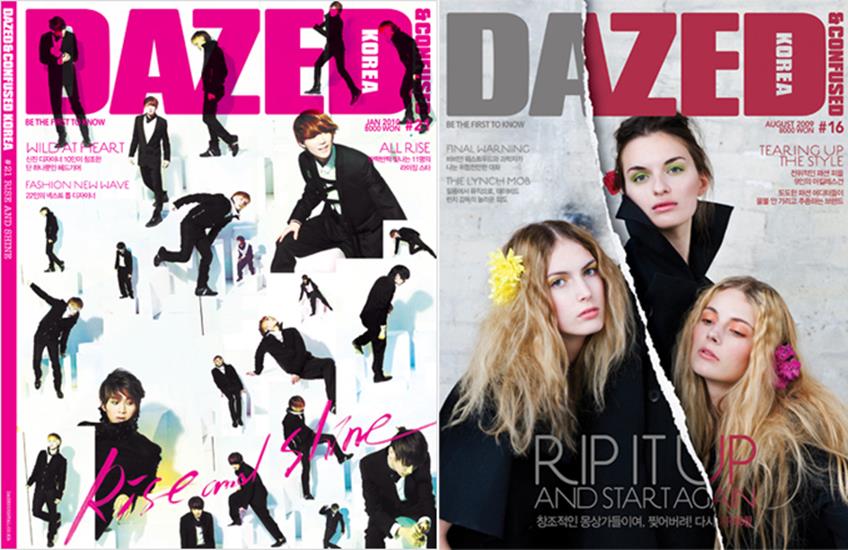
<DAZED> 매거진 디자인
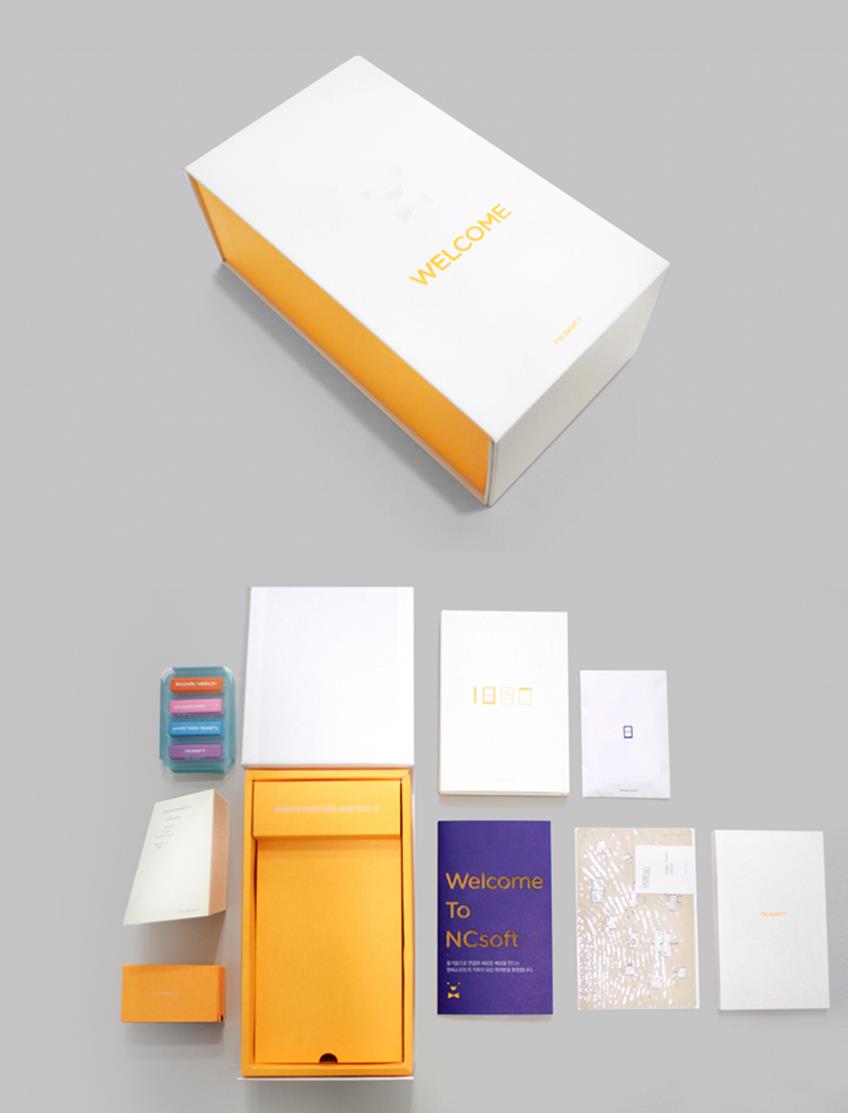
NC soft 신입사원 선물 디자인(패키지, 브로셔 등)
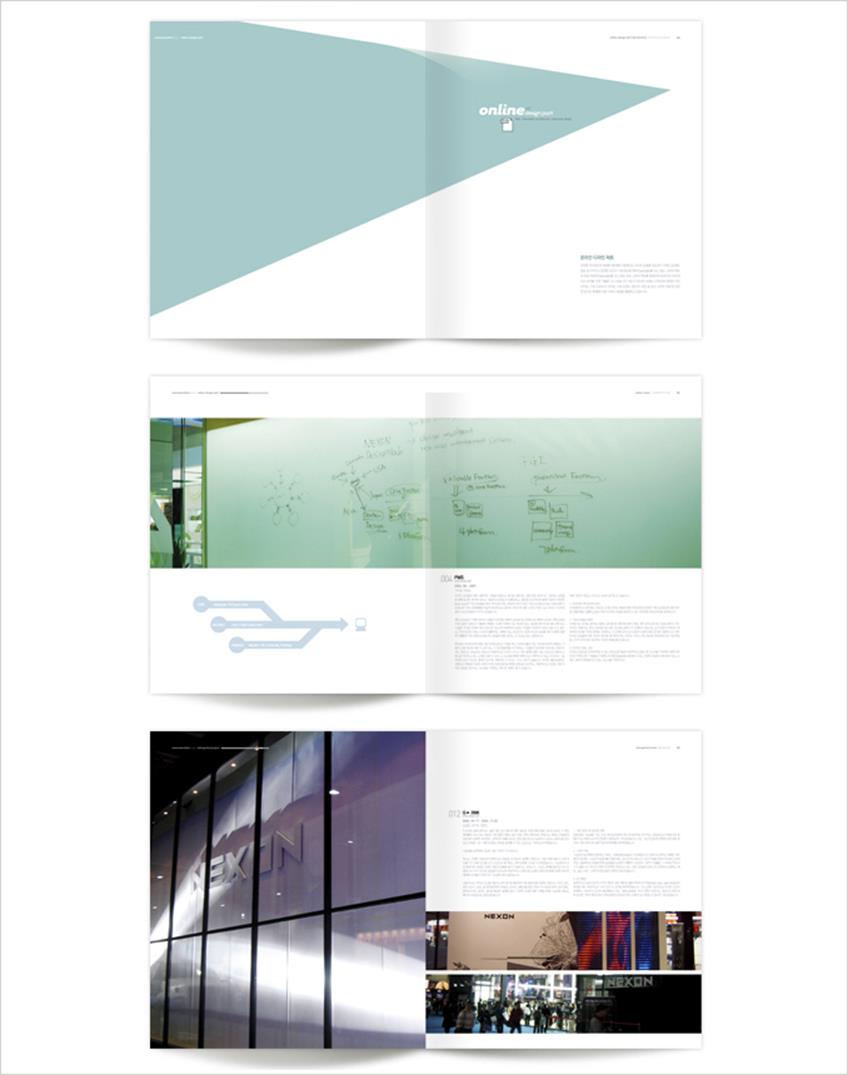
NEXON Annual Report
<블링>과 <데이즈드> 등 색이 명확하고 개성이 강한 매거진 디자인 작업을 하셨는데요. 각각의 잡지를 디자인하면서 가장 신경 쓴 부분은 무엇인가요?
<블링>과 <데지즈드>는 성향이 완전히 다른 매거진이에요. <블링>은 서브컬쳐 위주로 매달 스페셜 테마를 갖고 새로운 이슈나 아이템들을 독특한 컨셉과 다양한 아이디어로 접근합니다. 하지만 힘을 빼고 디자인하는 것이 주된 원칙이죠. 반면에 <데이즈드>는 책 한 권이 새로운 이슈로 진행되다 보니 디자인디렉팅을 넘어서 사진이나 전체 레이아웃을 모두 고민함과 동시에 힘을 많이 주는 디자인을 원칙으로 작업했어요. 도비라 페이지나 메인 섹션 이외에도 쉽게 간과할 수 있는 부분에 더 공을 들여서 디자인했죠. 에브리리틀씽의 의미와 통하는 부분이기도 합니다.
최근에 마무리한 작업을 소개해주세요.
삼성의 <딜라이트 어반그라운드 페스티벌(2012 D’LIGHT URBANGROUND)> 포스터 디자인을 진행했고, 얼마 전에 창간된 <캠퍼스10>이라는 캠퍼스 매거진 디자인을 아트디렉팅 하고 있습니다. 디자이너나 클라이언트 모두 신경 쓰지 못하고 놓치는 부분을 찾아 파고들어가는 게 제 스타일이에요. 저는 개인적으로 애플(Apple) 제품을 좋아해 많이 사용하는데요. 겉으로 들어나진 않지만 사용자를 배려해 만들어 놓은 기능을 우연히 발견하게 될 때 ‘이 기업이 나를 굉장히 배려해주고 있구나!’라는 좋은 기분을 느끼게 됩니다. 제 디자인도 그런 경험을 전해드릴 수 있으면 좋겠어요.
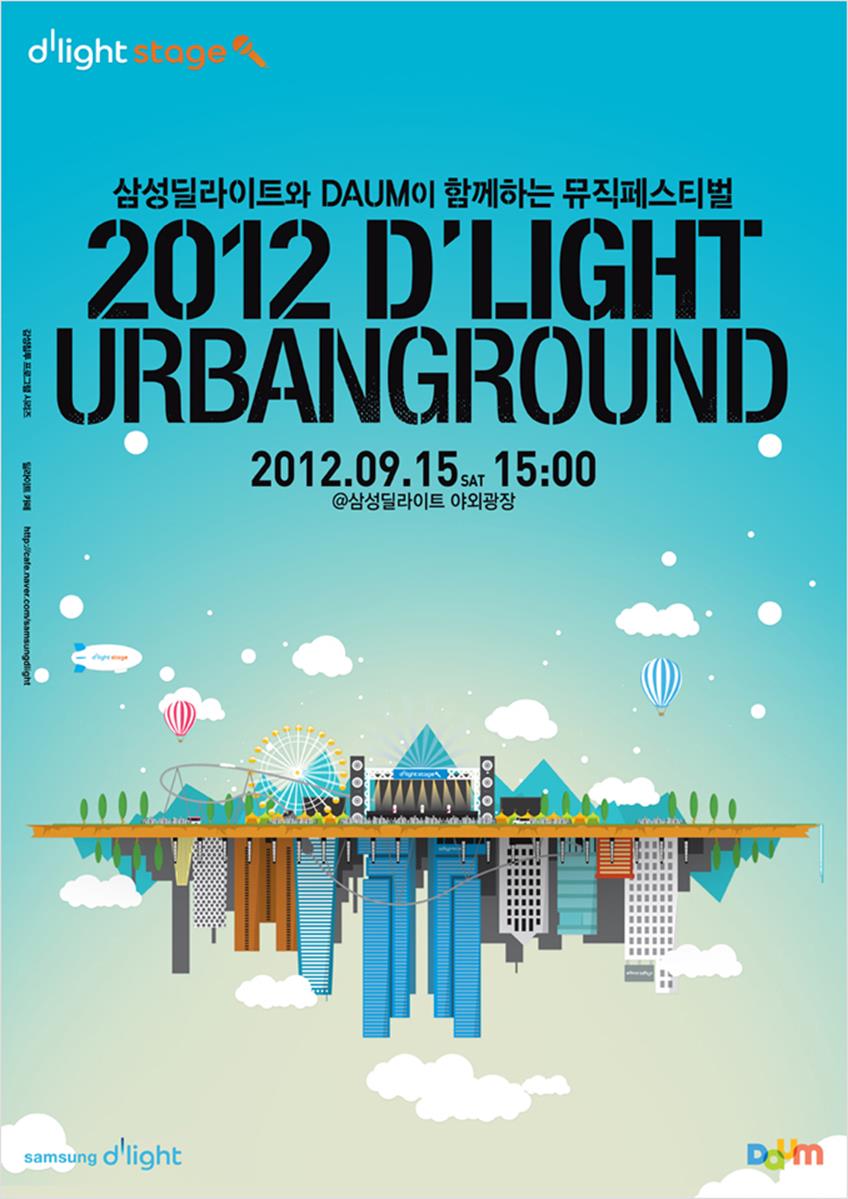
<2012 D’LIGHT URBANGROUND> 포스터 디자인
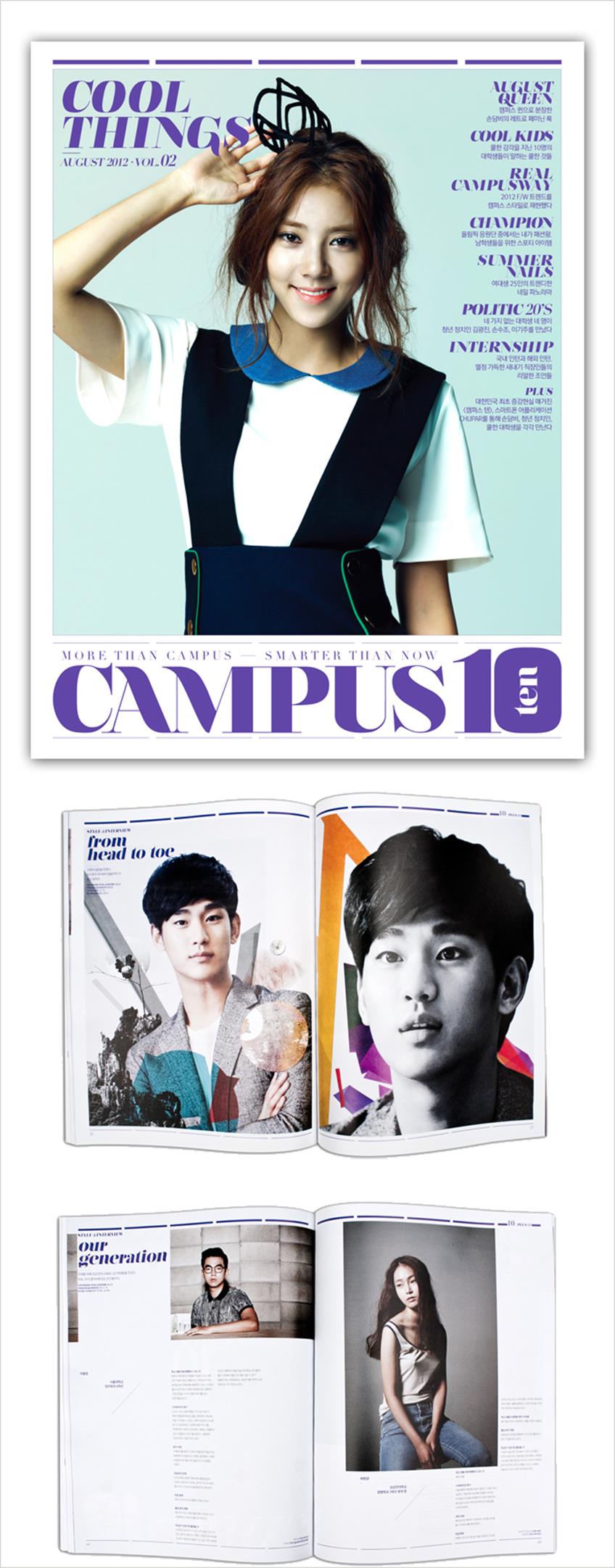
<CAMPUS10> 매거진 디자인
김창완밴드 음반 디자인 작업도 눈에 띄는데요.
겪어보신 분은 알겠지만 김창완 선생님은 다방면으로 굉장히 박식한 분이에요. 디자인 작업을 위해 여러 뮤지션을 만나 이야기를 나누게 되는데 음악과 미술, 음악과 디자인의 연결지점을 보게 됩니다. 음악적 컬러와 메시지를 그림처럼 명료하게 그려내는 뮤지션을 보면 굉장히 인상적이에요. 저는 그런 생각과 그림을 디자인적으로 완성도를 높이는 작업에 집중하게 되는 것이죠. 김창완 밴드의 분홍굴착기 작업도 비슷한 방식으로 진행되었어요. 굴착기나 공사장과 잘 어울리는 투박한 느낌의 스테실 작업 느낌이 나도록 음반 디자인을 하면서 한글과 영문 폰트를 새롭게 만들기도 했죠.
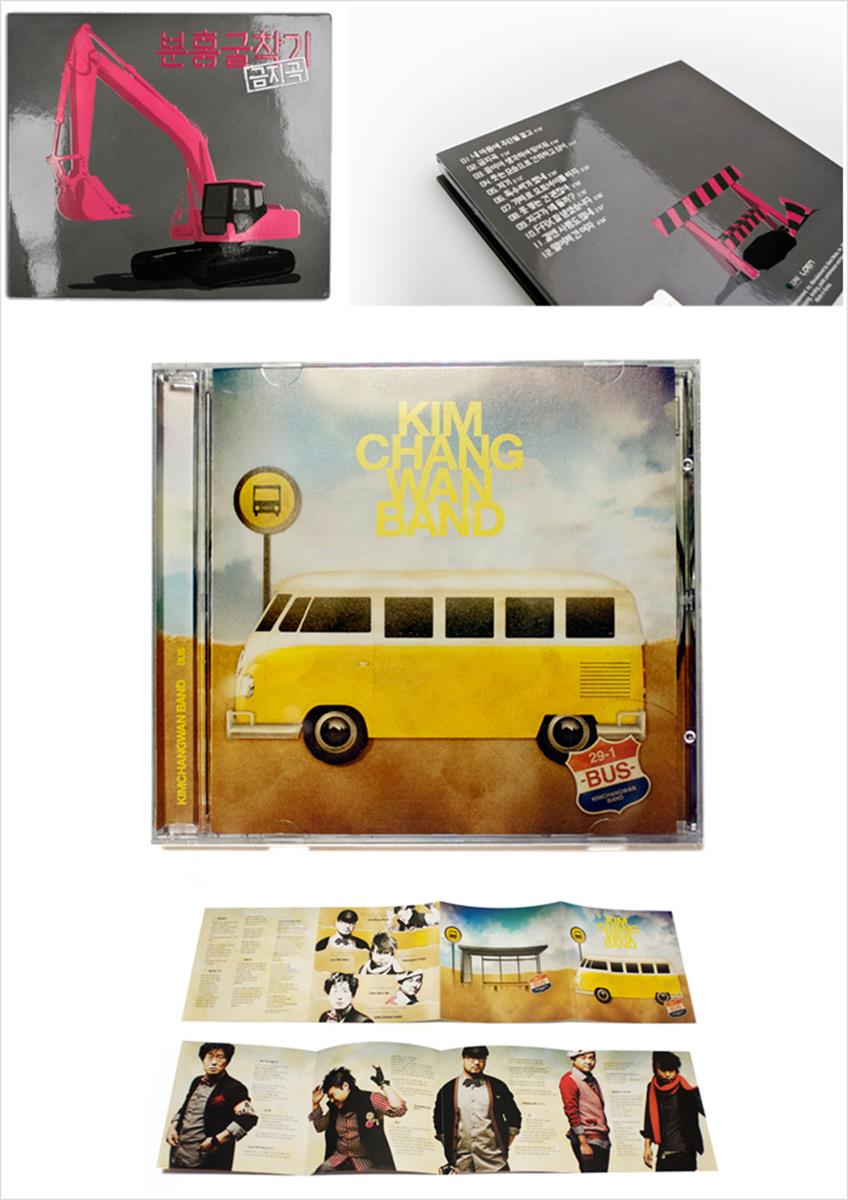
김창완밴드 앨범을 위한 일러스트와 폰트 디자인 작업
폰트에 대한 개인적인 취향은 어떤지 궁금합니다.
‘Helvetica’와 ‘Estilo’를 가장 많이 사용했어요. 헬베티카는 특별한 디자인 재료가 없이도 폰트만으로 디자인을 정리해주고 완성할 수 있는 강점이 있죠. 음식에 조금만 넣어도 맛을 내는데 큰 도움을 주는 ‘소금’과 같은 존재에요. 에스틸로는 한동안 <데이즈드>와 기타 디자인 작업에 많이 사용해온 서체에요. 다양하게 변형되는 스타일로 타이포그래피 작업이 되는 ‘설탕’ 같은 폰트죠.
글꼴 선정을 비롯해 한글 폰트와 라틴어 폰트의 조화, 크기나 자간 등을 결정하게 되는 기준이나 가이드가 있는지 궁금합니다.
글꼴 선정에 있어서 특별한 규칙은 없지만 본문 폰트는 고딕 계열을 기본으로 사용하고 있어요. 특별하게 폰트 작업에 규칙을 두는 것은 영문폰트와 한글폰트 혼용으로 사용했을 경우 높낮이가 달라지기 때문에 반드시 베이스라인을 조정해 준다는 점입니다. 그리고 한글 폰트에 들어가 있는 영문 폰트는 잘 사용하지 않는 편이에요. 영문 폰트는 별도로 지정해 정리하며 작업하는 편입니다.
본문을 제외한 타이틀 디자인에서는 주로 라틴 알파벳 폰트 활용 빈도가 높아 보이는데요. 특별한 이유가 있나요?
첫째로는 한글 폰트가 영문과 다르게 받침이 있어 애매한 공간이 많이 생기게 되어 한글로 스타일을 만들어 내는데 어려운 점이 많기 때문이에요. 두 번째로는 글 내용에서 느껴지는 분위기를 서체로 전달하도록 디자인하는데 한글은 고딕과 명조계열을 피해서 디자인 하기에는 영문만큼 다양성이 떨어지죠. 간혹 한글을 이용한 디자인을 하게 되면 기존 폰트 스타일을 해체하고 폰트를 변형해 타이틀로 새롭게 디자인하거나 캘리그라피로 작업하곤 합니다. 적용범위는 타이틀보다는 비주얼 작업이나 도비라 페이지가 되겠죠. 하지만 이전에 <데이즈드> 34호에서 한글 타이포그래피 디자인 기사에서 언급하기도 했지만 아무래도 “한글 타이포그래피 작업이 영문에 비해 제한적”이라는 고정관념에서 오는 문제가 가장 큰 것 같습니다.
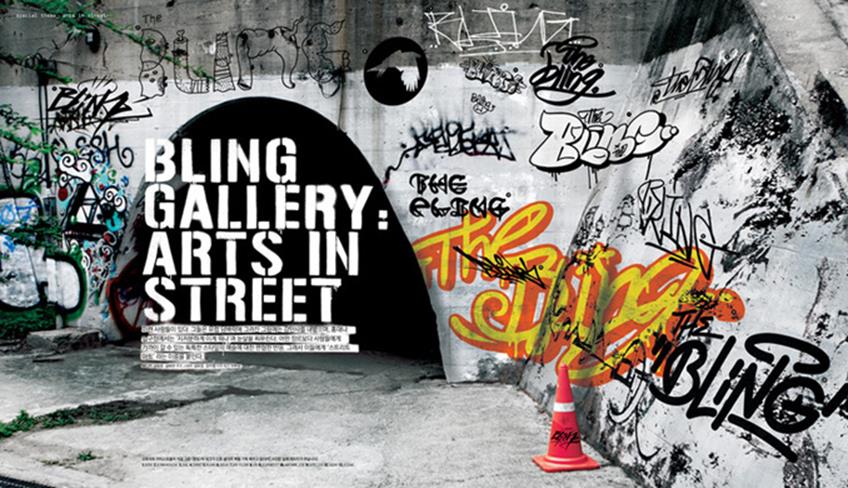
76호. 스트리트 문화를 소개하는 페이지에 실제로 그래피티 작업을 진행하여 소스로 활용했다.
<dazed> 25호. 신발끈을 활용하여 타이포그래피 작업을 했다
<dazed> 22호. 테이프를 이용해 타이포그라피 작업을 했다.
<dazed> 창간 포스터 캘리그라피 작업.
한글을 활용해 만든 타이포그래피 작품들. 제목은 알파벳을 해체해 한글로 표현했다.
직접 폰트를 만들어보고 싶은 생각은 없나요?
요즘 들어 다양한 한글폰트들을 접하게 되는데 외국의 유명한 폰트들 같이 명조나 고딕계열의 기본 형태를 유지하되 빈티지한 형태나 타이틀용 폰트를 작업해보고 싶어요. 현재는 앞서 말씀 드린 스텐실 느낌을 주는 타이포그래피 작업을 수작업으로 하고 있는데요. 이 작업을 폰트로 만들어 사용하고 싶긴 합니다.
디자인 작업에 어떤 것들이 도움을 주나요?
사진은 눈으로 보는 것과 달리 시간을 담아내는 도구라고 생각해요. 사진을 많이 찍고 보는 그 자체에서 도움을 받을 때가 많아요.
추천해주고 싶은 책이나 사이트가 있으면 말씀해주세요.
요즘 관심 갖고 보는 잇츠나이스댓(www.itsnicethat.com)이라는 웹사이트를 추천합니다. 다양한 작품들과 내용을 접할 수 있어요. 특이한 점은 오프라인 기반에서 웹 기반으로 전환되는 것이 아니라 반대로 웹 기반의 컨텐츠를 선별해 오프라인 매거진으로 만든다는 점이에요. 제가 모으고 있는 잡지 중 하나에요.
디자인, 사진, 일러스트, 영상 등 독창적인 작품들로 가득한 잇츠나이스댓(www.itsnicethat.com)
마지막으로 에리브리틀씽의 계획은요?
얼마 전 창간된 <캠퍼스10>(www.campus10.co.kr)이 기존 캠퍼스 매거진과는 다른 방향으로 자리잡는데 제 디자인이 일조했으면 좋겠습니다. 그리고 신인가수 위주로 음반 디자인 작업을 지속적으로 진행할 예정이에요. 실험적인 새로운 방법으로 접근할 생각입니다. 지켜봐 주세요.